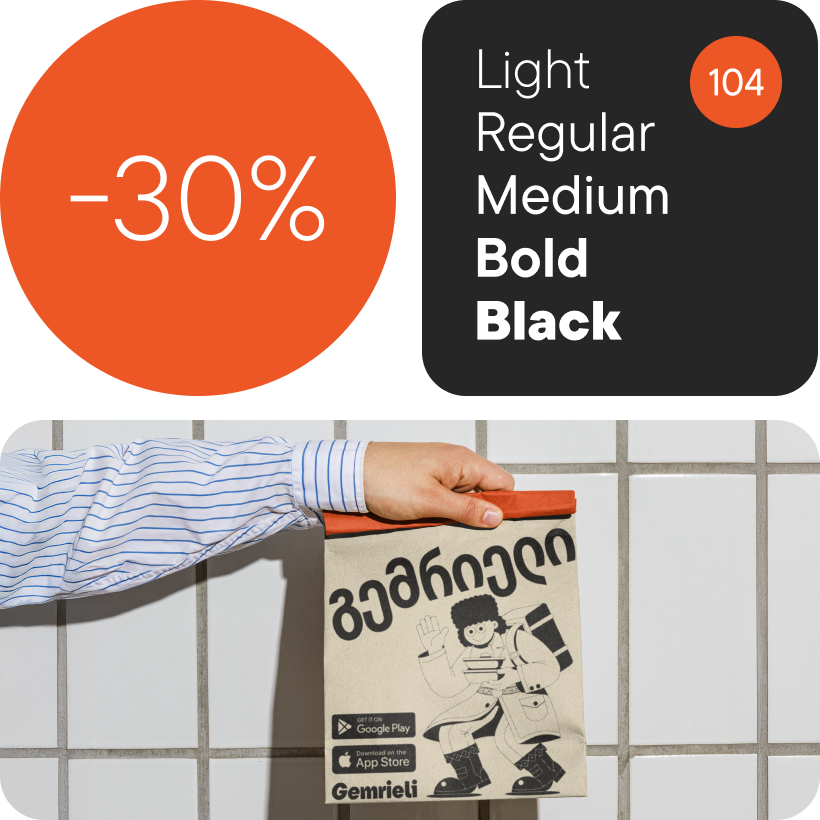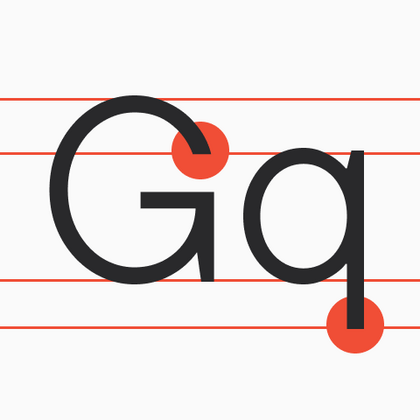
Шрифты без засечек (Гротески)
Если вы ищете нейтральный и лаконичный шрифт, который выглядит современно и стильно, обратите внимание на шрифты без засечек (гротески). Они используются повсеместно — на сайтах и в мобильных приложениях, в печатной продукции и брендинге. В коллекции TypeType много разнообразных гротесков — от нейтральных до ярких. Выбирайте подходящий вам вариант из нашей подборки.
На сегодняшний день гротески — самые современные и востребованные шрифты. Чаще всего шрифтовые гарнитуры именно этого стиля становятся интерфейсными у брендов с громким именем, украшают популярные сайты, смотрят на зрителей с постеров, афиш и витрин магазинов.
Простые на первый взгляд, аккуратные и универсальные, они захватили мир и стали новым правилом хорошего тона. Использовать гротеск в своих проектах — значит понимать современные тенденции и располагать пользователя на диалог.
Не удивительно, что в обширной коллекции шрифтов TypeType именно гротески завоевали сердца миллионов. Бестселлеры ТТ Нормс Про (TT Norms® Pro) и ТТ Коммонс Про (TT Commons™ Pro), не менее востребованные ТТ Ховс Про (TT Hoves Pro), ТТ Фирс Нью (TT Firs Neue) и ТТ Форс (TT Fors) — все эти шрифты относятся к гротескам.
Помимо геометрических, выделяют старый, гуманистический и неогротеск (эволюция классического гротеска с более проработанной пластикой и читаемостью). Общими характерными чертами всех групп выступают отсутствие засечек, широкая область применения и универсальность.
Старыми называют первые гротески, зародившиеся ещё в викторианскую эпоху. Такие шрифты хоть и не имели засечек, обладали довольно экстравагантным внешним видом по сравнению с поздними гротесками.
Неогротески или новые гротески появились позднее старых. Они выглядели намного изящнее и строже своих предшественников. Эти шрифты функциональнее и крайне адаптивные под любую сферу применения. Неогротески неконтрастные и моноширинные.
Гуманистические гротески, как можно угадать из названия, уходят от строгости в сторону гуманизма. В них чувствуется влияние каллиграфии, появляются отсылки к засечкам и динамика. Как правило, это разноширинные шрифты с высоким контрастом штрихов. Имеют настоящее курсивное начертание, то есть знаки не просто обретают наклон, но и могут менять форму. В коллекции TypeType вы можете познакомиться с гуманистическими гротесками ТТ Веллингтонс (TT Wellingtons) и ТТ Коралс (TT Corals).
Геометрические гротески — это настоящие рабочие лошадки в мире шрифтов, функциональные и универсальные. Они не обладают ярким визуальным характером, поэтому могут подходить практически для любой области применения. Эстетично смотрятся на печатной продукции, идеальны в вебе, подходят в качестве интерфейсного шрифта.
Универсальность геометрических гротесков обусловлена тем, что форма знаков построена на основе простых геометрических фигур. Чаще всего, это неконтрастные разноширинные шрифты. Этот вид шрифтов подходит как для заголовков, так и для написания больших пластов текста.
Геометрические гротески широко представлены в коллекции TypeType. К этой категории относятся и легендарные ТТ Нормс Про и ТТ Коммонс Про, и востребованные ТТ Лэйкс (TT Lakes), ТТ Ховс Про и ТТ Форс.
Каждый из гротесков в коллекции TypeType обладает оригинальностью и собственными особенностями, однако все они дружелюбны к пользователю и функциональны. В каждом из наших гротесков есть большое количество начертаний, так что можно выбрать для своего проекта самый подходящий или купить лицензию на несколько.
Более того, в некоторые из них мы добавили вариативное начертание, например, в ТТ Нормс Про и ТТ Коммонс Про. Благодаря этому вы сможете выбрать идеальную вариацию шрифта.
TT Polihaus — экспериментальный гротеск, который на первый взгляд кажется обычным, а затем разбирается на части, превращаясь в трафаретный узор.
TT Chocolates — изящный гуманистический гротеск сo сбалансированными пропорциями, близкими к классическим. Шрифт с приятным дружелюбным характером, который интуитивно воспринимается как что-то знакомое.
TT Dott — экспериментальный пиксельный гротеск, в котором за основу пикселя взят круг. Это пластичный и необычный акцидентный шрифт, вызывающий ассоциации одновременно с вышивкой и техно-вечеринками.
TT Supermolot Neue — технологичный модульный гротеск с футуристическим настроением и мощным функционалом. Яркость его характера сочетается с универсальностью применения.
TT Commons™ Classic — универсальный геометрический гротеск для широкого круга задач.
TT Runs — это выразительный шрифт, который идеально впишется в проекты со спортивной тематикой. При этом гарнитура отлично подойдет и для других современных проектов: после обновления сфера ее применения значительно расширилась.
TT Severs — это геометрический гротеск с ярко выраженными элементами внутренних скруглений. Отличительной особенностью TT Severs является необычная форма внутренних овалов, которая отсылает нас к стилю традиционной арабской письменности.
TT Gertika — геометрический гротеск с динамичным характером и танцующим ритмом. Идея шрифта зародилась из леттеринга на американском плакате второй половины 30-х годов.
TT Biersal — акцидентный гротеск со свободным, озорным и авантюрным характером. Отправной точкой для его создания послужил немецкий плакат начала 30-х годов. Мы хотели сохранить не только пропорции, но и ощущение небрежности, живости леттеринга из референса.
TT Paplane — акцидентный сквадраченный гротеск. Так, характерные черты этого гротеска — сквадраченные формы, 45-градусные срезы и обтекаемые внешние контуры.